看综艺节目的时候经常会看到屏幕上有各种各样的字幕,就是我们在平时看电视的时候也是这样的,一些字幕字体飒是好看,而且有的字体一眼看上去就是大方得体,有的则是带有一定趣味性的,那么这些好看的字体都是来自于哪里呢?
其实很多的综艺节目的字幕字体都是来源于字体视界的,例如暑期很火的一档综艺节目《我们是真正的朋友》,其中就有义启魔音体在里面。因为字体视界中是有非常多类别的字体,满足了不同的字体的需求,不管是高品质的印刷字体还是手写体或者个性字体都可以满足。字体视界传承的是中华印刷文字的艺术,从文字的笔划上入手,让每一个笔划细节都可以看得到圆润、锋利,都可以品味到内涵。在响应了现代化的字幕要求,结合更多人的视野的同时,不再是以单纯的黑体、宋体等字体来完善自身,而是提供了更多种类的字体。
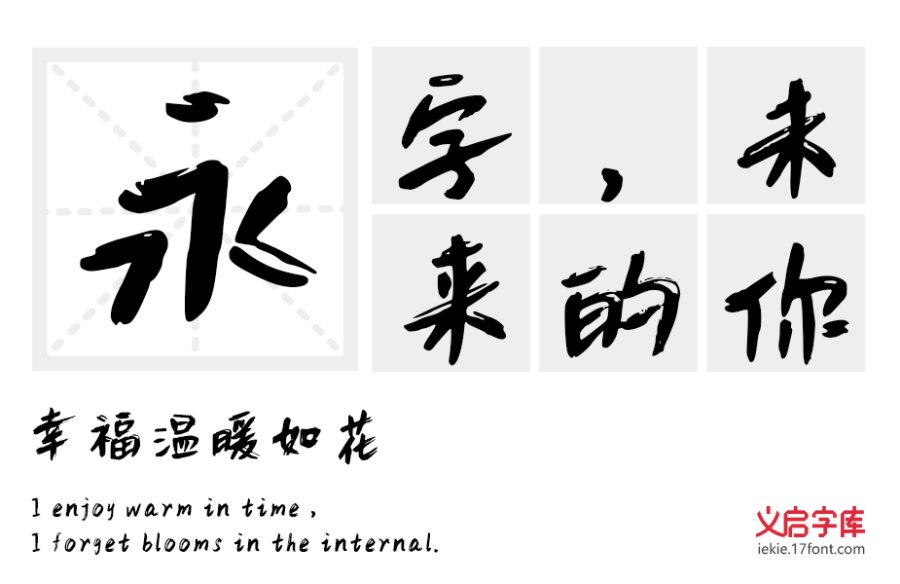
现在很多的综艺节目字幕字体已经不满足传统的黑体、宋体或者是简体,它们更偏向于符合综艺节目内容的字体,像是文艺范的,嘻哈风的,还有很多不同的类型的,在字幕字体上字体视界中的抹茶体、白鹿体、紫水晶体等都曾经在综艺节目字幕上出现过,不同的字幕带来的视觉是不同的,在针对性的进行综艺节目字幕的制作的时候,也是考虑到这其中的细节,所以带来的字幕效果更有看点。众观国内外综艺节目,不同的字幕字体,也带来的是不同的效果。所以综艺节目中的字幕字体也是颇有学问的。